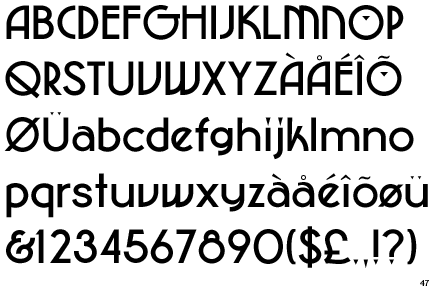
Coney Island Schrift
... bin neu hier, kann mir jemand helfen? Ich bin auf der Suche nach der Schrift vom Vergnügungspark Coney Island (http://www.coneyislandfunguide.com/)
Hat jemand eine Idee welche das sein könnte?
Ich bin nach langer Suche auf eine ähnliche Schrift (NewGarden Bold) gestossen.
die Basis könnte die
sein.
Auf jedem Windowsrechner sollte die Desdemona zu finden sein ... hat allerdings den Nachteil, dass sie nur als Outlineschrift vorhanden ist.
Bei mir gibt’s die nicht. :?